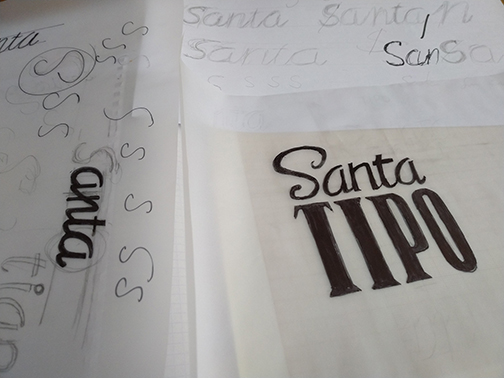
El logo de Santatipo
No hace mucho me preguntaban de dónde sale el logo de Santatipo.
SantatipoAntes de dar forma al proyecto en si, algo que me obsesionaba era darle una imagen única. Quería dotarle de personalidad y para ello necesitaba ver muchas imágenes de Santander. Y es una de esas cuando de algún modo la inspiración llegó. Fue al ver la foto de 1913, de las Joyería Losada donde vi algo que me atrajo. Y fue la «S» aparte de su tipografía modernista.
A partir de ahí se diseño el resto en base a esa tipo. Añadir el claim «entre tipos y calles» es toda una declaración de intenciones del trasfondo del proyecto: Tipos como elementos tipográficos y Tipos como personajes. Entre Calles, porque es ahí donde se respira la identidad de las mismas. Pateando, mirando e imaginando.
En 2017 dentro del Certamen de Tipos, asistí a un taller del genial Andreu Bailus donde trabajamos una identidad en base de la Tipografía. De ahí salió un concepto nuevo, más fresco y que mezcla varias referencias. Entre ellas los rótulos de la Ferretería Jiménez Díaz (hoy el Gallofa de Hernán Cortés).
Ejercicio del taller de Andreu Bailus
PD: en más de una ocasión me han dicho que si es como el de Agua Solares. Y si tiene algún elemento en común 🙂